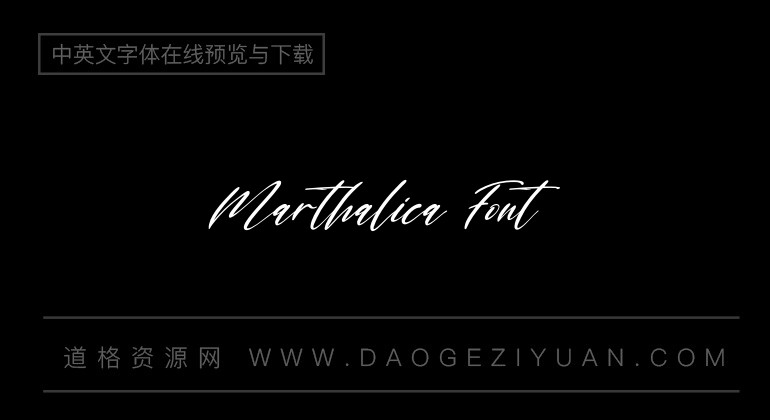
Marthalica Font 是一种手写风格的字体,具有很高的装饰性和艺术性。这种字体的特点是笔画流畅,线条柔和,有一定的书法感觉。Marthalica Font 适用于各种设计场景,如印刷品、海报、标志、包装、网站设计等。它的阅读性也很好,适合用于长文章和段落文字。Marthalica Font 可以用于个人和商业用途,是一种非常受欢迎的字体之一。内容介绍
Marthalica Font是一款非常不错的手写艺术字体,具有很好的视觉感,适合于文化类的宣传设计、商业类品牌的广告和产品包装设计以及个性化文字排版等较多场景。